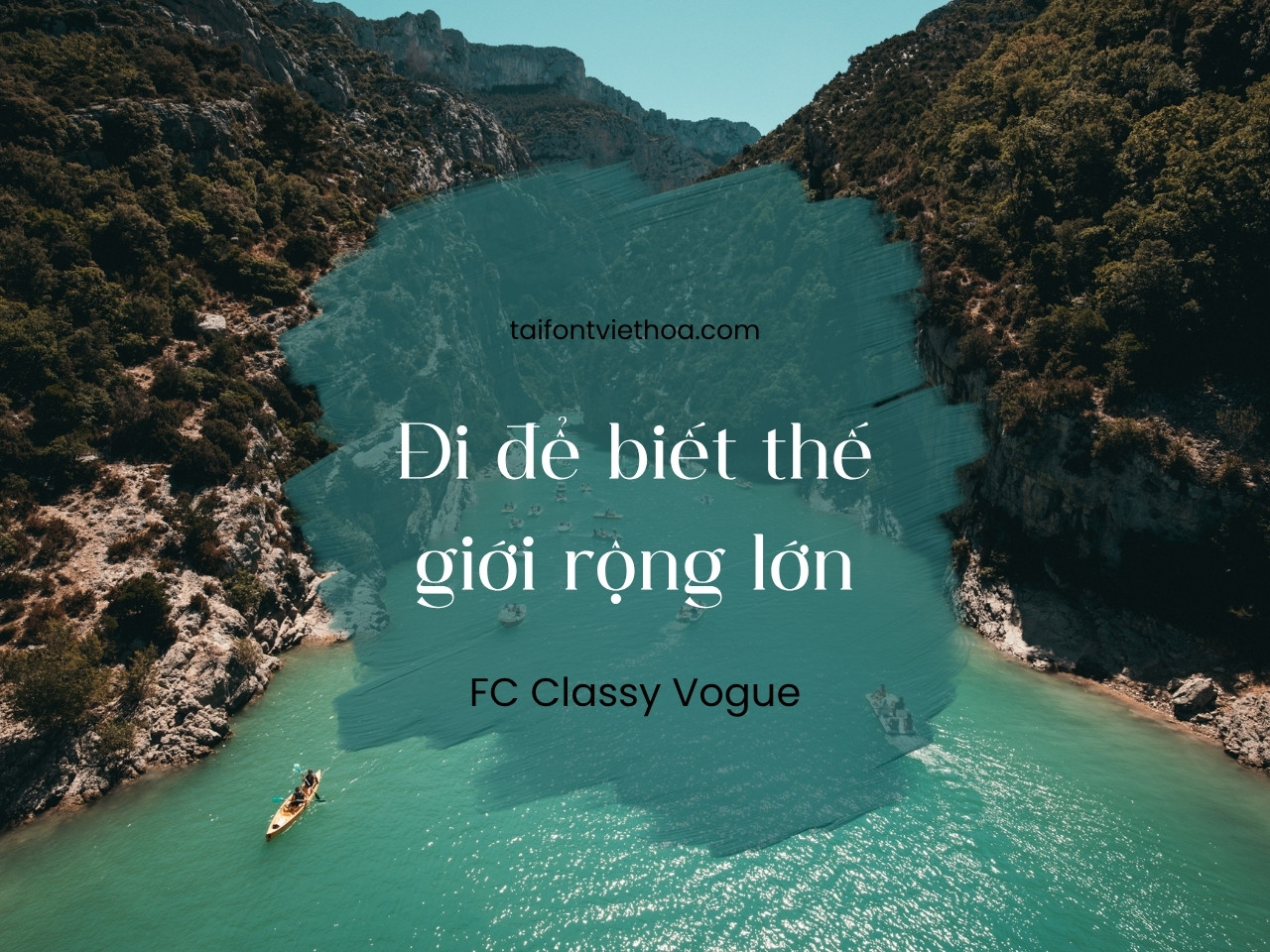
Font việt hóa FC Classy Vogue
Giới thiệu về font Classy Vogue và phiên bản Việt hóa
FC Classy Vogue là phiên bản Việt hóa từ font gốc “Classy Vogue” – một kiểu chữ serif tinh tế được thiết kế bởi TemplateZuu Studio, nổi bật trên các nền tảng chia sẻ font như Creative Market và FontBundles. Mang đậm tinh thần thời trang cao cấp và phong cách editorial châu Âu, Classy Vogue được sử dụng rộng rãi trong các tạp chí, bộ nhận diện thương hiệu thời trang, mỹ phẩm cao cấp và thiết kế truyền thông đòi hỏi sự thanh lịch, chỉn chu. Font gốc hỗ trợ hơn 90 ngôn ngữ, bao gồm đầy đủ bảng chữ Latinh mở rộng và các glyphs đặc biệt để tăng tính ứng dụng quốc tế.
Phiên bản FC Classy Vogue đã được cộng đồng Font Chuẩn Việt hóa đầy đủ, tinh chỉnh lại các chi tiết Unicode nhằm hỗ trợ tiếng Việt một cách hoàn hảo. Toàn bộ dấu thanh và ký tự tiếng Việt đều được xử lý mượt mà, giữ trọn phong cách thiết kế thanh lịch vốn có. Font này được taifontviethoa.com chọn lọc và chia sẻ nhằm phục vụ cộng đồng designer Việt cần một phông chữ có thẩm mỹ cao, dễ dàng áp dụng trong các dự án branding, thiết kế in ấn và quảng cáo cao cấp.
Đặc điểm thiết kế và khả năng ứng dụng thực tế
Classy Vogue sở hữu cấu trúc serif cổ điển nhưng mang tính hiện đại nhờ vào đường nét mềm mại, kết hợp độ tương phản cao giữa các nét chính – phụ. Các ký tự có phần thân hẹp, kéo dài và được thiết kế theo phong cách editorial, làm nổi bật sự cao cấp, tinh tế mà vẫn giữ được tính dễ đọc. Font còn đi kèm các ligatures thời thượng và glyphs mở rộng, giúp gia tăng khả năng trình bày sáng tạo trong các bản thiết kế.
FC Classy Vogue lý tưởng cho các thiết kế bao bì mỹ phẩm, thương hiệu thời trang nữ, logo ngành nội thất cao cấp, editorial, tạp chí, thiệp cưới sang trọng và các chiến dịch quảng cáo đòi hỏi định vị thương hiệu cao cấp. Đặc biệt, đây là font không thể thiếu cho các dự án liên quan đến làm đẹp, spa hoặc truyền thông luxury.